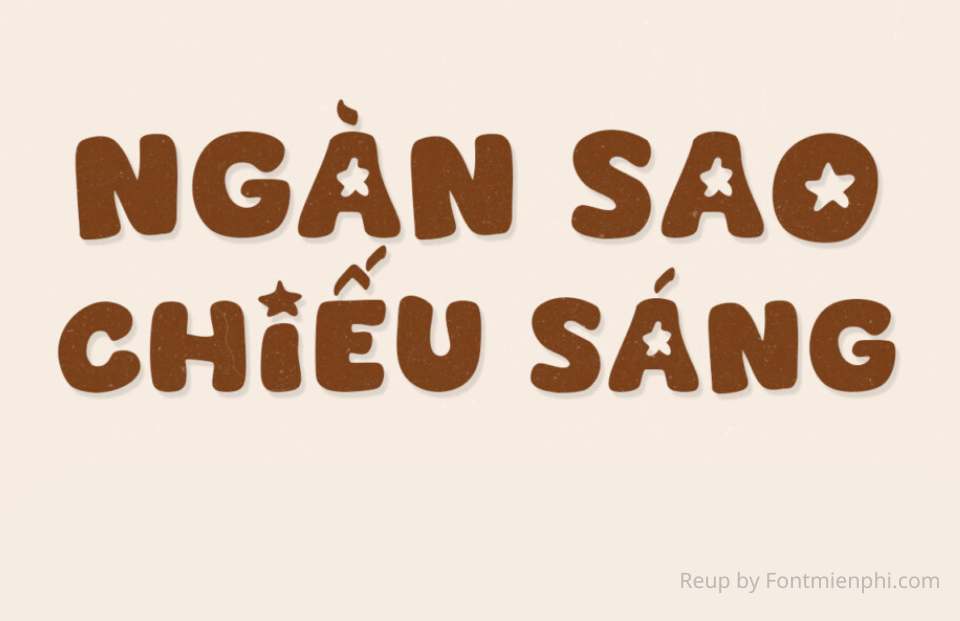
Trong lĩnh vực thiết kế đồ họa, việc tìm kiếm một phông chữ (font) vừa có tính thẩm mỹ cao, vừa hỗ trợ gõ tiếng Việt không bị lỗi dấu luôn là ưu tiên hàng đầu. Nếu bạn đang tìm kiếm một “làn gió mới” cho các dự án sáng tạo của mình, font Việt hóa 1FTV VIP Singsong chính là sự lựa chọn không thể bỏ qua.
Font Việt hóa 1FTV VIP Singsong là gì?
1FTV VIP Singsong là một bộ phông chữ cao cấp đã được đội ngũ 1FTV (1Font) tinh chỉnh và Việt hóa hoàn chỉnh. Sở hữu những đường nét thiết kế độc đáo, kết hợp hài hòa giữa sự mềm mại và hiện đại, bộ font này mang đến cảm giác thanh lịch, nghệ thuật nhưng vẫn vô cùng dễ đọc. Đây là bộ font thuộc nhóm “VIP”, nghĩa là nó được đầu tư rất kỹ lưỡng về mặt kerning (khoảng cách chữ) và dấu câu tiếng Việt.
Những Ưu Điểm Nổi Bật Của Bộ Font Việt Hóa 1FTV VIP Singsong Tuyệt Đẹp
Không phải ngẫu nhiên mà font 1FTV VIP Singsong Việt hóa lại được cộng đồng designer săn đón. Dưới đây là những lý do khiến bộ font này trở nên đặc biệt:
Hỗ trợ tiếng Việt chuẩn 100%: Các dấu câu (hỏi, ngã, nặng…) được thiết kế đồng bộ với nét chữ gốc, không xảy ra tình trạng lệch dấu hay lỗi font trên các phần mềm thiết kế như Adobe Illustrator, Photoshop hay Canva.
Đường nét tinh tế, tính thẩm mỹ cao: Font mang phong cách nghệ thuật, giúp bản thiết kế của bạn trông sang trọng và chuyên nghiệp hơn.
Tính đa dụng (Versatility): Phù hợp với nhiều phong cách thiết kế từ cổ điển, lãng mạn cho đến hiện đại, trẻ trung.
Ứng Dụng Của Font 1FTV VIP Singsong Trong Thiết Kế
Với vẻ đẹp linh hoạt, 1FTV VIP Singsong có thể được ứng dụng trong vô số các ấn phẩm đồ họa, tiêu biểu như:
Thiết kế Logo & Bộ nhận diện thương hiệu: Tạo sự khác biệt và đẳng cấp cho các thương hiệu thời trang, mỹ phẩm, spa.
Typography & Poster: Làm nổi bật các câu quote, tiêu đề bài viết hay poster phim ảnh.
Ấn phẩm sự kiện: Hoàn hảo để sử dụng làm font chữ cho thiệp cưới, thư mời hoặc các banner quảng cáo sự kiện sang trọng.